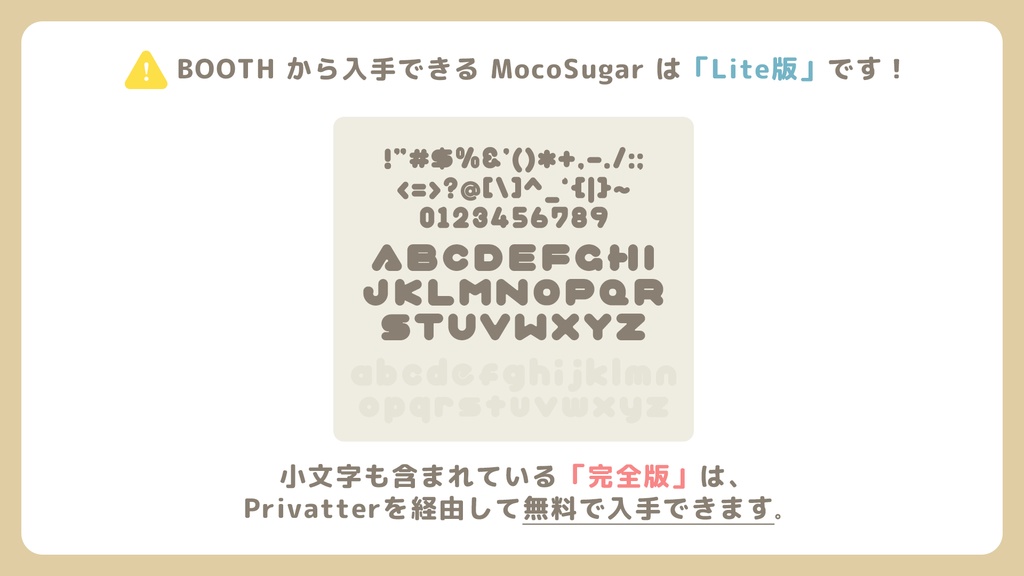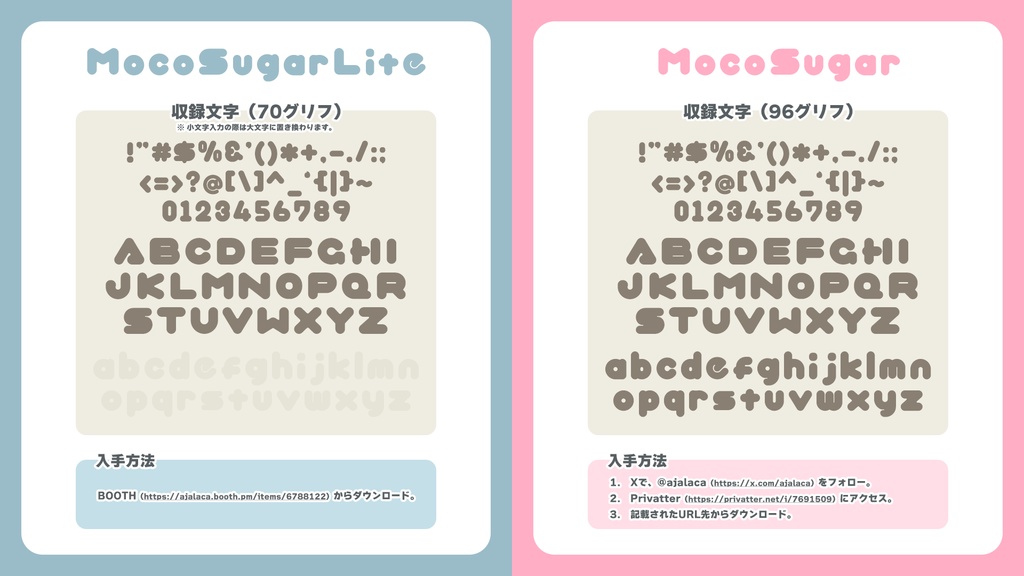
【フリーフォント】MocoSugar(Lite版)
モコモコでかわいい雰囲気に似合う欧文フリーフォントです 🧁 ※ BOOTHでは、大文字のみを収録した「Lite版」を公開しています。 ============================================= MocoSugarLite Regular 制作:アジャラカ( https://twitter.com/ajalaca ) イラスト:ろどりさん( https://x.com/rororodly ) ============================================= ■ 小文字を収録した「完全版」を入手するには? ・ぷらいべったー( https://privatter.net/i/7691509 )に記載のリンク先よりどなたでも入手できます。 ・閲覧には、Xにて @ajalaca をフォローしていただければ確認いただけます。 ■ ライセンス ・個人利用・商用利用にかかわらず、どなたでも無料でお使いいただけます。 ・配布の際はSIL Open Font Licenseに基づいてリリースする必要があります。 ・SILライセンスについては、以下のURLよりご確認ください。 https://licenses.opensource.jp/OFL-1.1/OFL-1.1.html ■ 禁止行為 ・「SIL Open Font License Version 1.1」以外のライセンスで再配布すること。 ・フォントファイル自体を単体で販売すること。